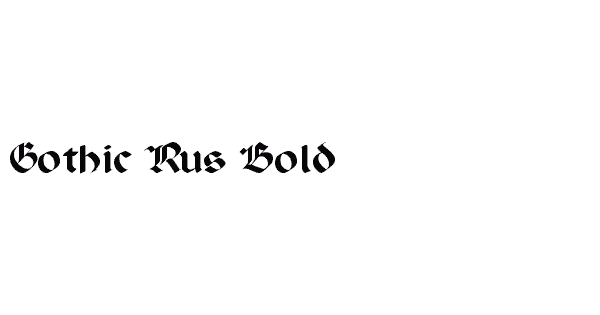
Шрифт gothicrus: GothicRus Medium шрифт
Готический русский шрифт Ogilvie Cyr
Прикольный рисованный русский шрифт DS Down Cyr
Кириллический русский шрифт DS Eraser Cyr
Бесплатный русский шрифт TauernCTT
Бесплатный кириллический шрифт с шумом MatterhornCTT
Растянутый русский шрифт с эффектом ветра Slipstream
Красивый рисованный кириллический шрифт palette
Креативный русский шрифт в стиле игры Packman
Русский кириллический шрифт с тенью a_CampusOtl3DShad
Качественный русский шрифт EpsilonCTT
Зимний русский шрифт со снегом на буквах Zanesennyj
Креативный кириллический шрифт Kashmir